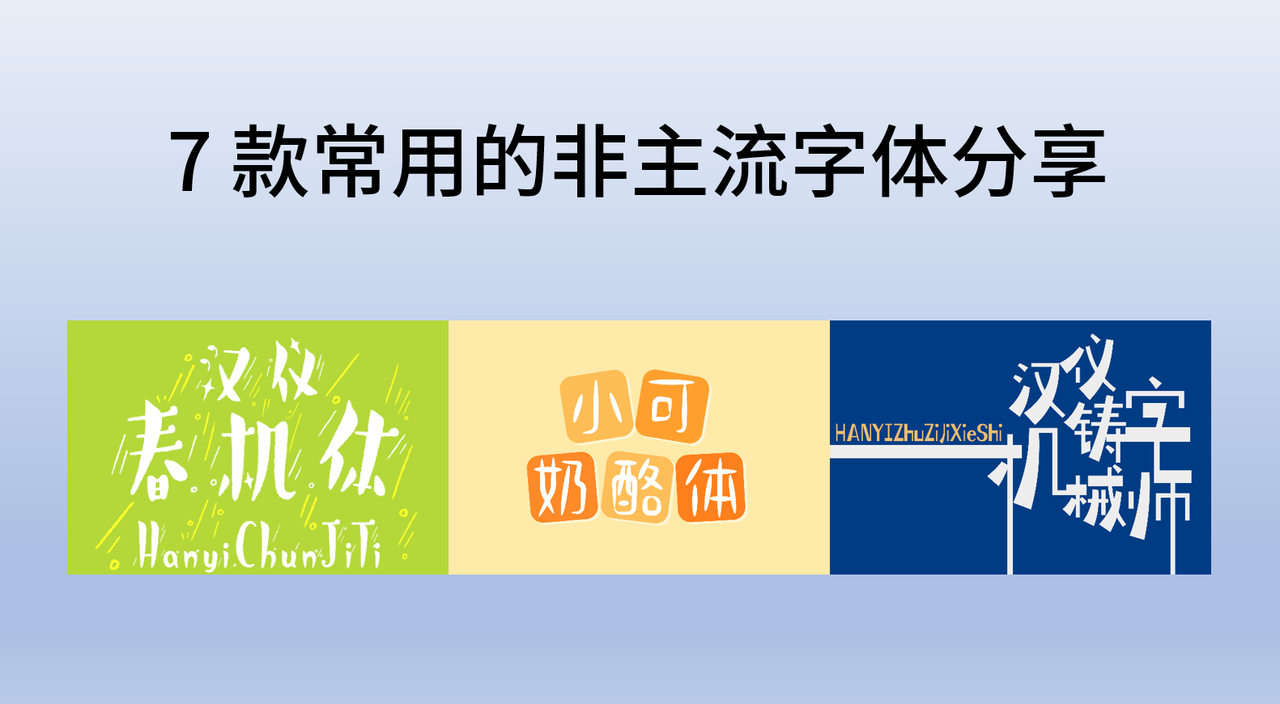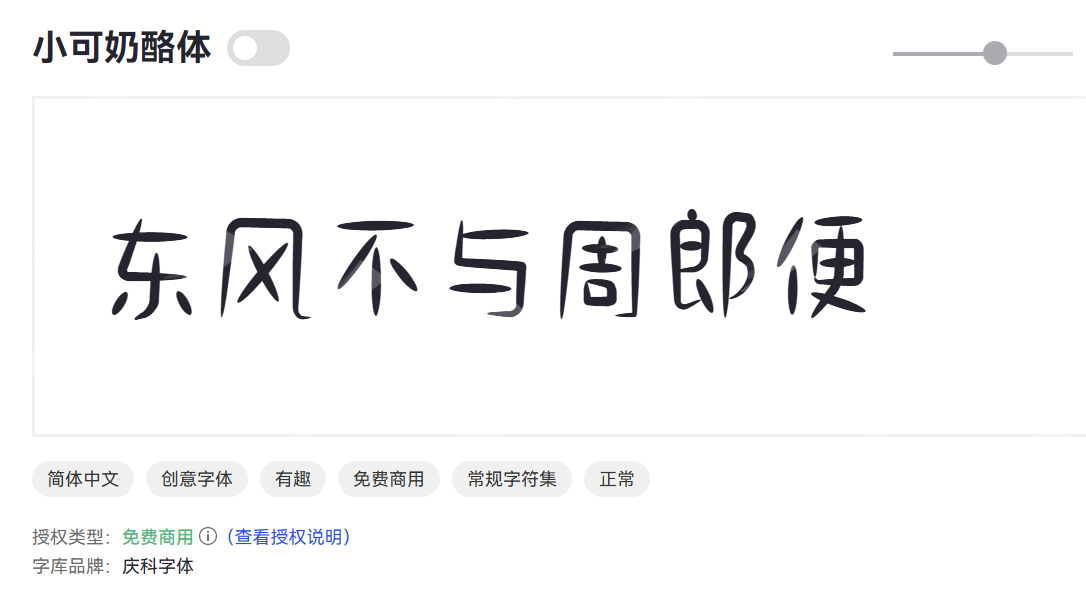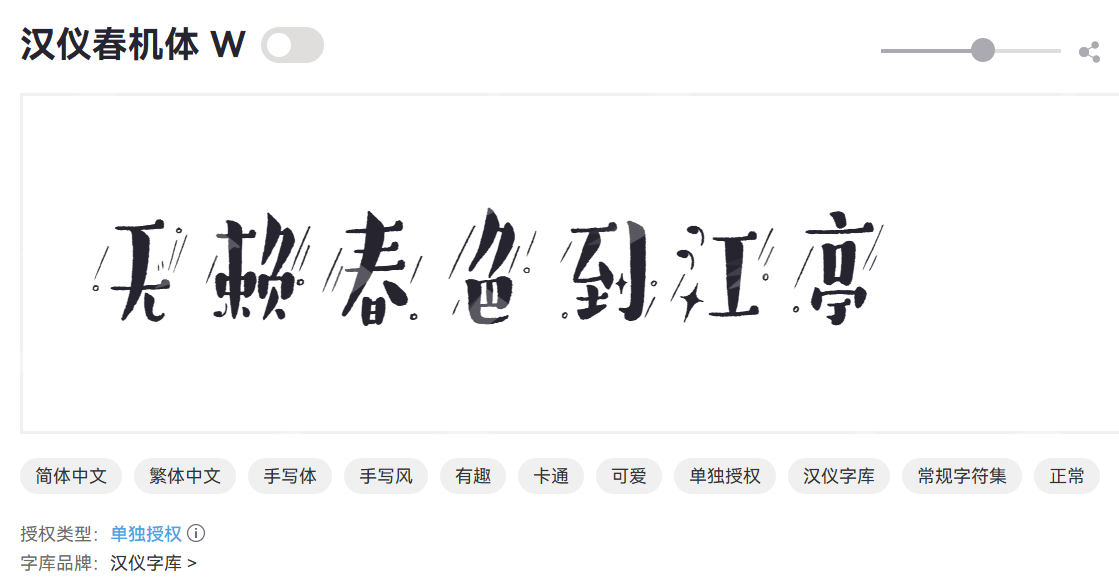
非主流字体大全,7 款常用的非主流字体分享
非主流字体不像我们日常生活中随处可见的系统默认字体那样规整、低调,而是充满了强烈的个性、独特的风格和不羁的创意。我个人非常喜欢非主流字体,本文重点给大家分享 7 款我常用的非主流字体,并会告诉大家是否可以免费商用。
新愚公迷茫体
新愚公迷茫体是一款风格独特的非主流艺术字体。它突破传统字体的规整束缚,充满人文情怀与艺术个性。
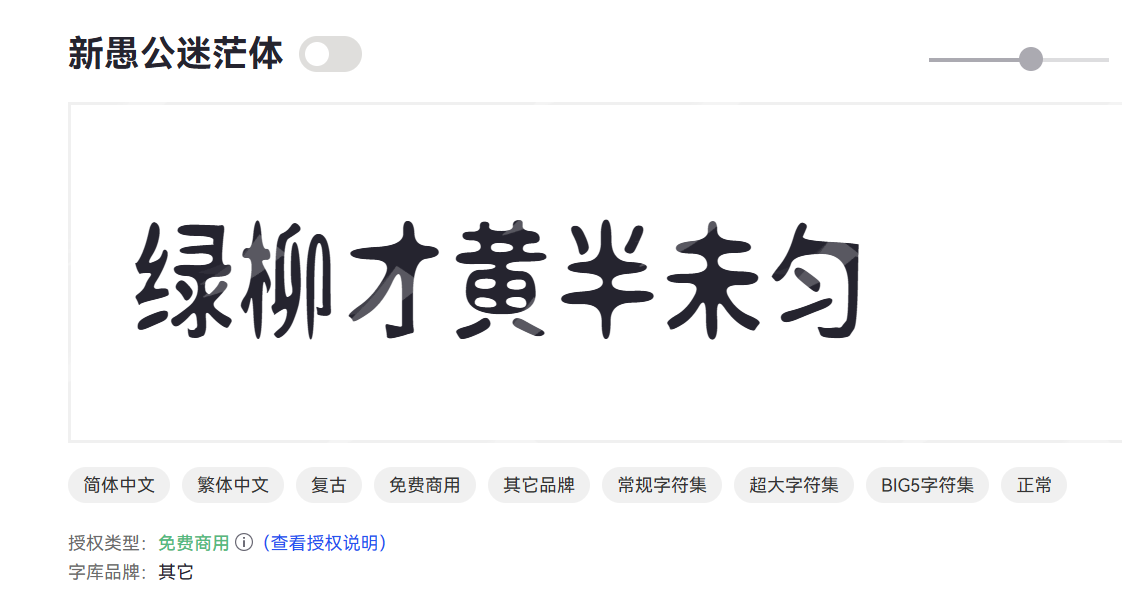
字体特点
- 带有手写痕迹,边缘或粗细略有变化。
- 整体呈现一种“迷茫”或“笨拙”的独特美感。
- 充满艺术气息与不羁的独立精神。
使用场景
- 艺术设计:画展、独立电影、戏剧海报、艺术装置的标题。
- 文创产品:个性化T恤、帆布包、笔记本等独立设计师品牌。
- 特定主题:哲学思辨、探险、探索未知等主题的宣传。
- 小众品牌:追求独特、反主流、有故事性的品牌Logo。
小可奶酪体
小可奶酪体是一款以“奶酪”为设计灵感的可爱风格字体。它将奶酪的圆润、饱满、柔软的特性融入到笔画与结构中,旨在营造一种甜美、温暖、充满童趣的视觉感受,让人感到轻松愉悦。
字体特点
- 形似融化的奶酪,边缘柔软,充满弹性。
- 整体呈现萌趣、Q弹的视觉效果。
- 传递轻松、愉悦、温暖的幸福感。
使用场景
- 儿童品牌:童装、玩具、儿童教育、母婴产品的Logo与宣传。
- 食品饮料:零食、甜点、乳制品、饮品等包装设计。
- 卡通漫画:动画片标题、漫画对话框、表情包设计。
- 文具礼品:手账、贺卡、贴纸、个性化礼品等创意周边。
汉仪春机体
汉仪春机体是一款充满生机与活力的手写风格字体。它以春天万物复苏、蓬勃向上的意象为灵感,将手写体的自然流畅与现代设计的清新感融合。
字体特点
- 整体布局不拘一格,充满手写般的亲切感。
- 传递轻松、愉悦、充满生命力的情感。
使用场景
- 社交媒体:微信公众号、微博、小红书等平台图文标题与配字。
- 文创设计:手账、贺卡、文具、礼品包装等创意产品。
- 活动宣传:节假日、亲子活动、市集等营造轻松氛围的海报。
Aa全息黑体
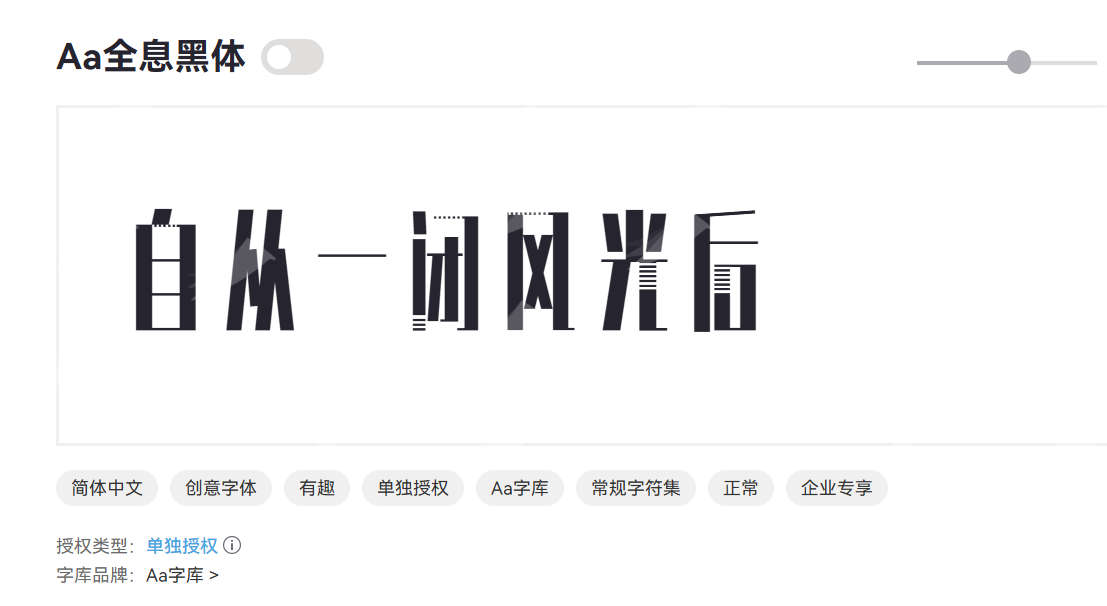
字体特点
- 笔画硬朗,融入几何切割或光影效果的视觉元素。
- 现代黑体的基础之上,注入数字和空间感。
- 整体风格前卫、醒目,充满未来主义色彩。
使用场景
- 科技产品:智能手机、电脑、家用电器等产品的UI界面与宣传。
- 游戏动漫:科幻题材游戏标题、UI设计、角色命名。
- 数字媒体:元宇宙、区块链、人工智能等概念的视觉呈现。
- 潮流时尚:未来主义风格服装品牌、电子音乐节海报。
汉仪铸字机械师
汉仪铸字机械师是一款充满工业复古美学的字体。它从传统铸字工艺和机械时代的工业设计中汲取灵感,展现出一种硬朗而富有力量的独特风格。
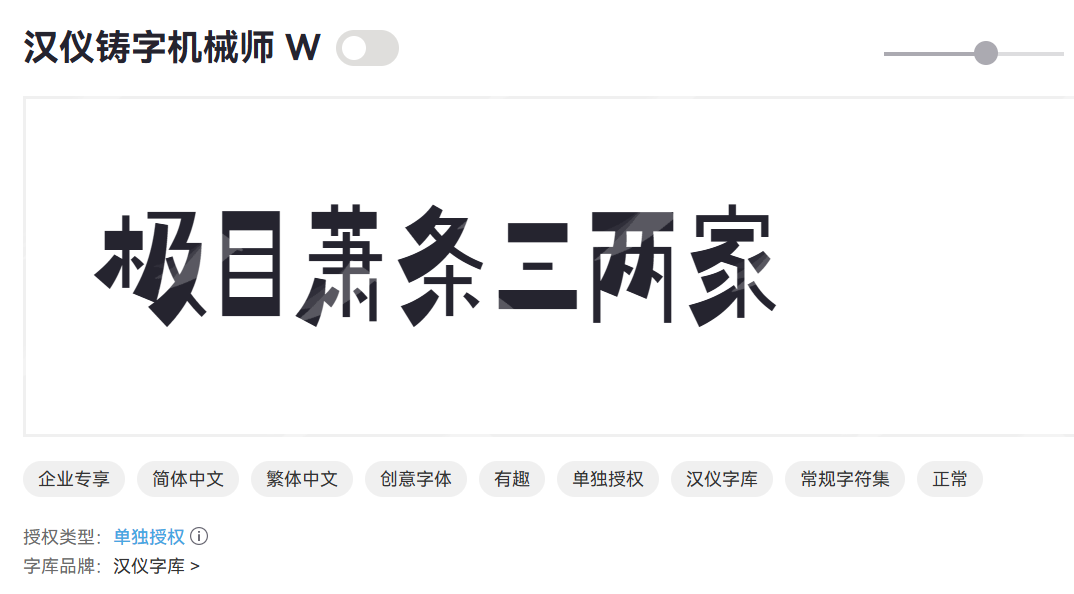
字体特点
- 笔画方正有力,带有铸字机或机械时代的痕迹。
- 如同机械制造般一丝不苟,充满秩序感。
使用场景
- 工业制造:机械、工具、汽车配件等行业的品牌Logo与宣传。
- 复古主题:蒸汽朋克、手工坊、复古咖啡馆、酒吧招牌。
- 男士品牌:男士理容、皮具、户外用品等强调质感的品牌。
- 文创产品:活字印刷、匠人精神、老物件等相关文创设计。
龚帆拙朴体
龚帆拙朴体是一款回归自然、充满手作温度的艺术字体。
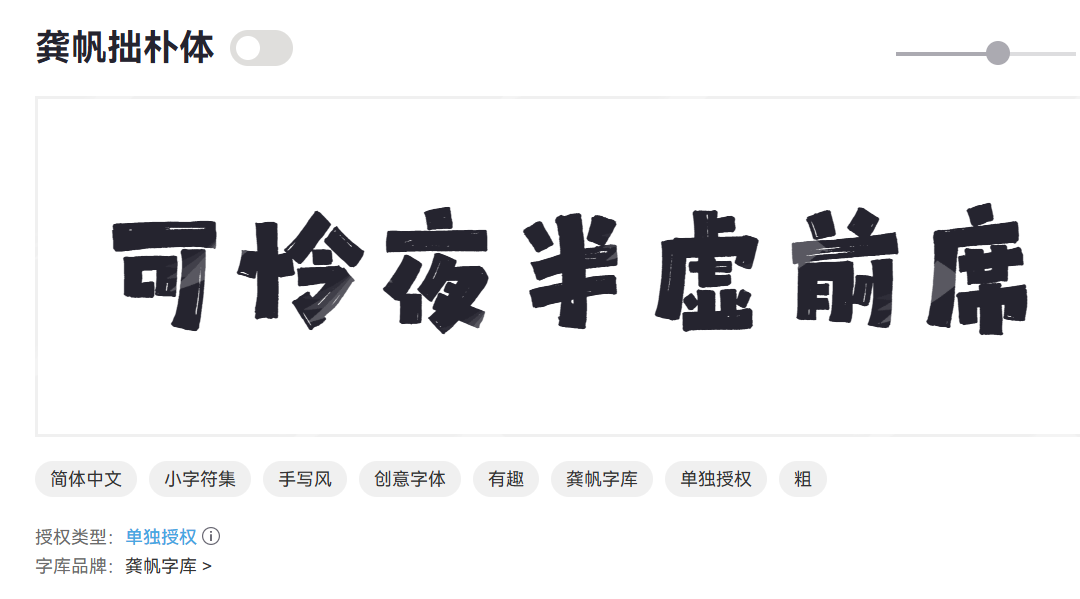
字体特点
- 呈现原始、自然的粗糙感与手作痕迹。
- 传递纯粹、自然、不加修饰的美学理念。
使用场景
- 传统文化:茶道、陶瓷、木艺、非遗文化等品牌的Logo与宣传。
- 自然生态:有机食品、环保产品、民宿、乡村旅游的视觉设计。
- 艺术展览:国画、书法、雕塑等艺术作品的标题与介绍。
上首朋克体
上首朋克体是一款充满叛逆与不羁精神的潮流艺术字体。
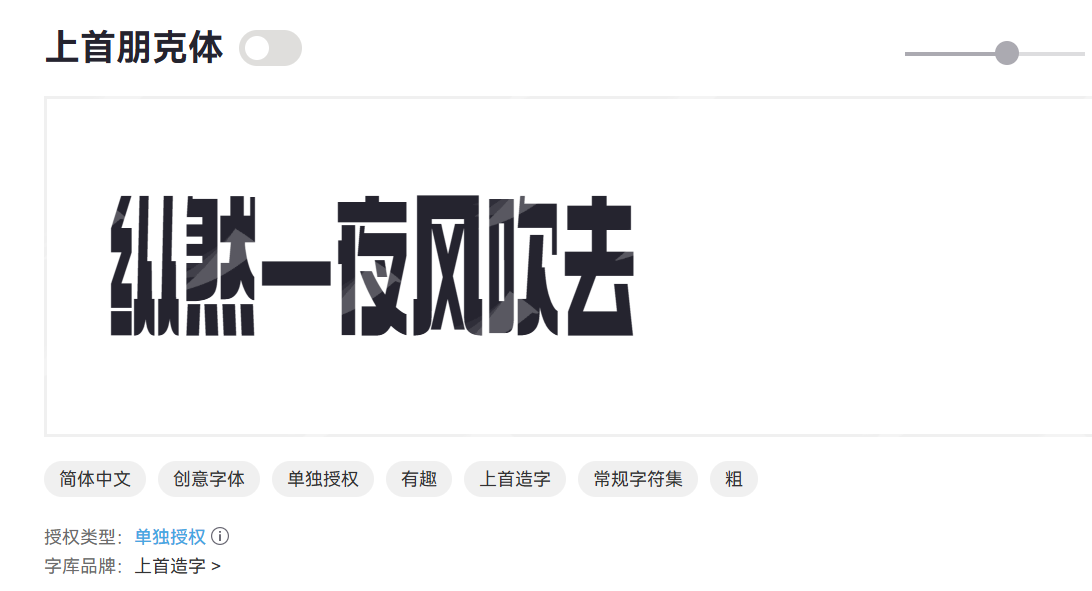
字体特点
- 线条边缘常有断裂、涂抹或刮擦的痕迹。
- 整体风格强烈,充满爆发力和街头气息。
使用场景
- 潮流品牌:服装、鞋帽、配饰等街头潮牌的Logo与海报。
- 音乐文化:摇滚乐队、音乐节、演唱会海报、专辑封面。
- 极限运动:滑板、跑酷、涂鸦等亚文化领域的宣传。
- 娱乐媒体:游戏、动漫、电影中需要营造反叛氛围的标题。